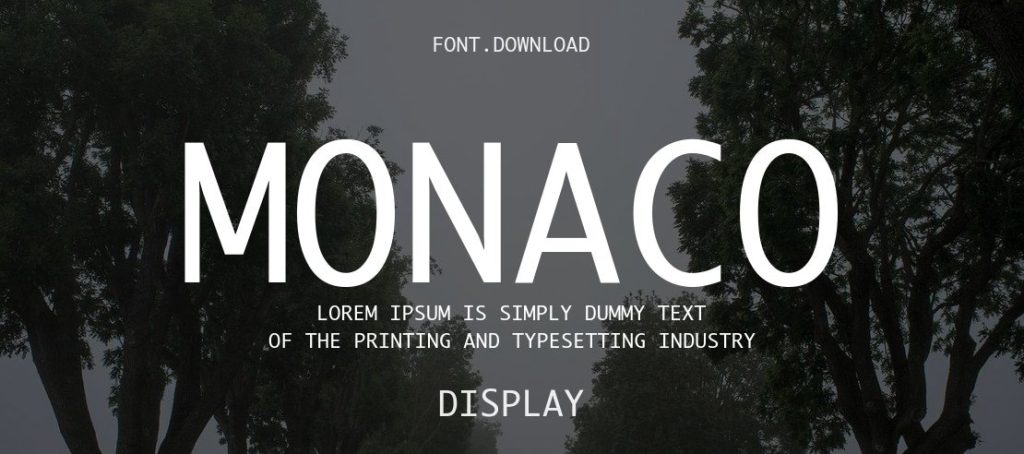
Tác giả: Susan Kare
Ngày phát hành: 1983
Phân loại: Đơn giản
Kiểu chữ: Monospace
Font Monaco là một kiểu chữ đơn giản thuộc bộ font chữ không chân được sử dụng phổ biến rộng rãi trong lập trình, nổi bật với tính dễ đọc và thiết kế đơn giản. Được phát triển bởi Apple, Monaco thường xuất hiện trong các môi trường phát triển tích hợp (IDE) và trình soạn thảo mã nhờ khả năng hiển thị rõ ràng các ký tự, đặc biệt là khi làm việc với các đoạn mã phức tạp. Font Monaco có kiểu dáng monospaced (khoảng cách giữa các ký tự bằng nhau), giúp lập trình viên dễ dàng theo dõi và kiểm tra mã nguồn, đồng thời giảm thiểu sai sót. Với thiết kế tinh tế và chức năng vượt trội, Font Monaco là lựa chọn lý tưởng cho các chuyên gia công nghệ thông tin.